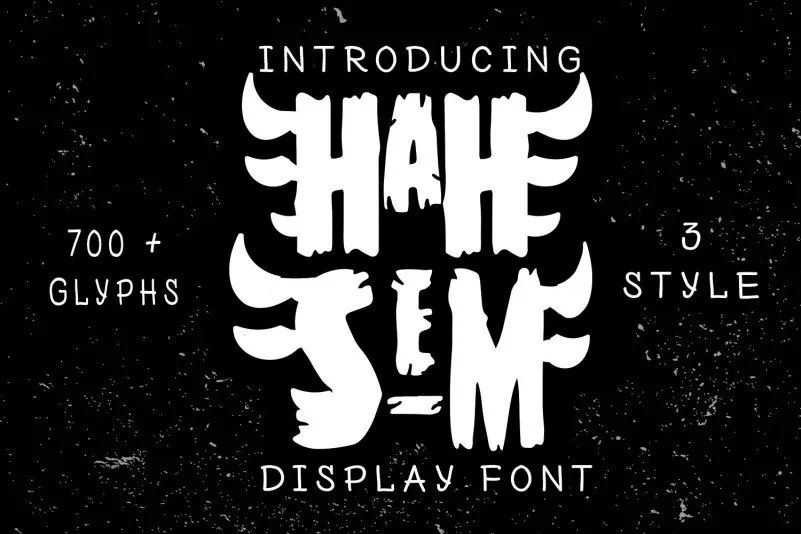
Hah Sem Display Font – Download Grátis
Hah Sem é uma nova fonte display que inspira-se no personagem uka uka do game Crash Bandicoot, famoso por ser parte integrante da cultura dos tempos pré-históricos. Esta fonte bold e vigorosa transmite a essência de um mundo onde dinossauros e humanos conviviam em harmonia. Com seu design único que faz homenagem às tradições e costumes do passado, Hah Sem oferece uma experiência visual impactante para qualquer projeto de design gráfico que busque resgatar memórias fascinantes da era pré-histórica. Ideal para adicionar um toque distinto a marcas, cartazes e materiais promocionais, Hah Sem é o tipo certo para capturar olhares e criar uma conexão emocional com seu público.